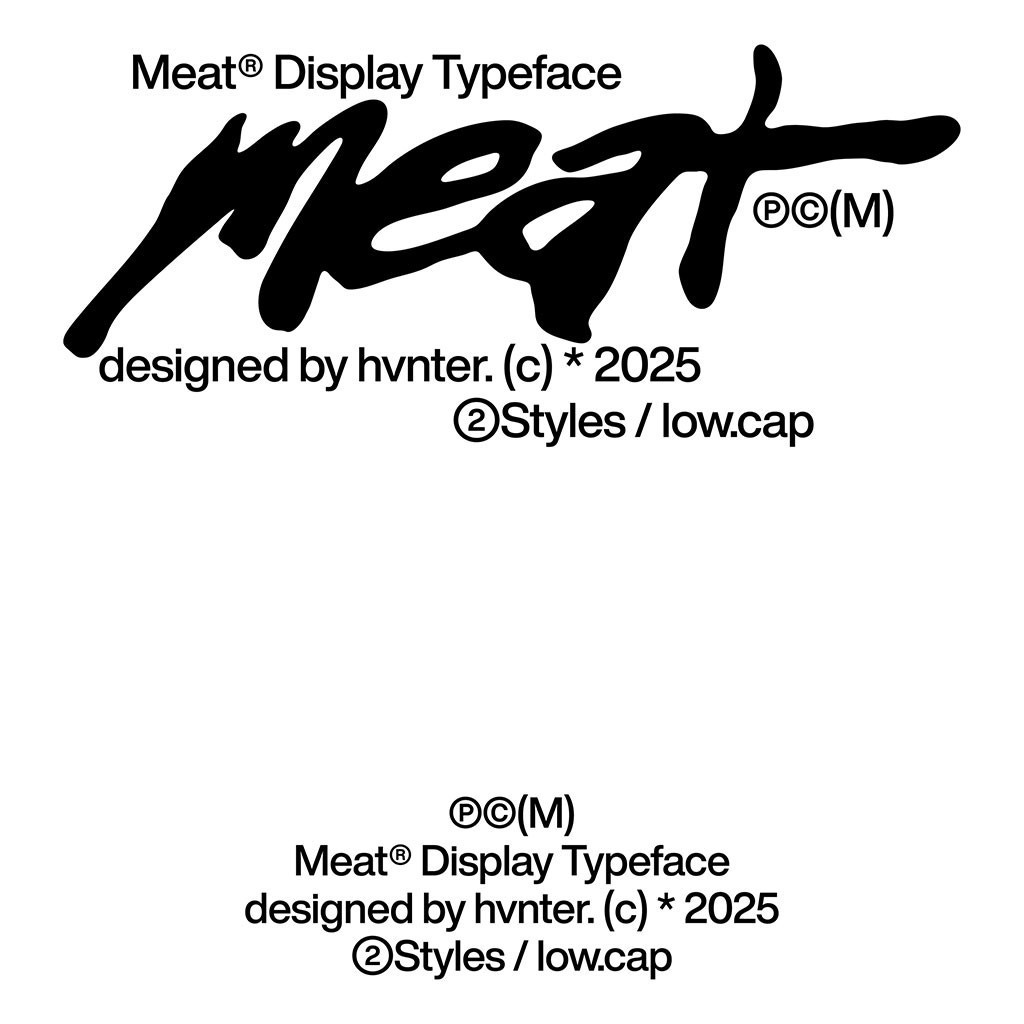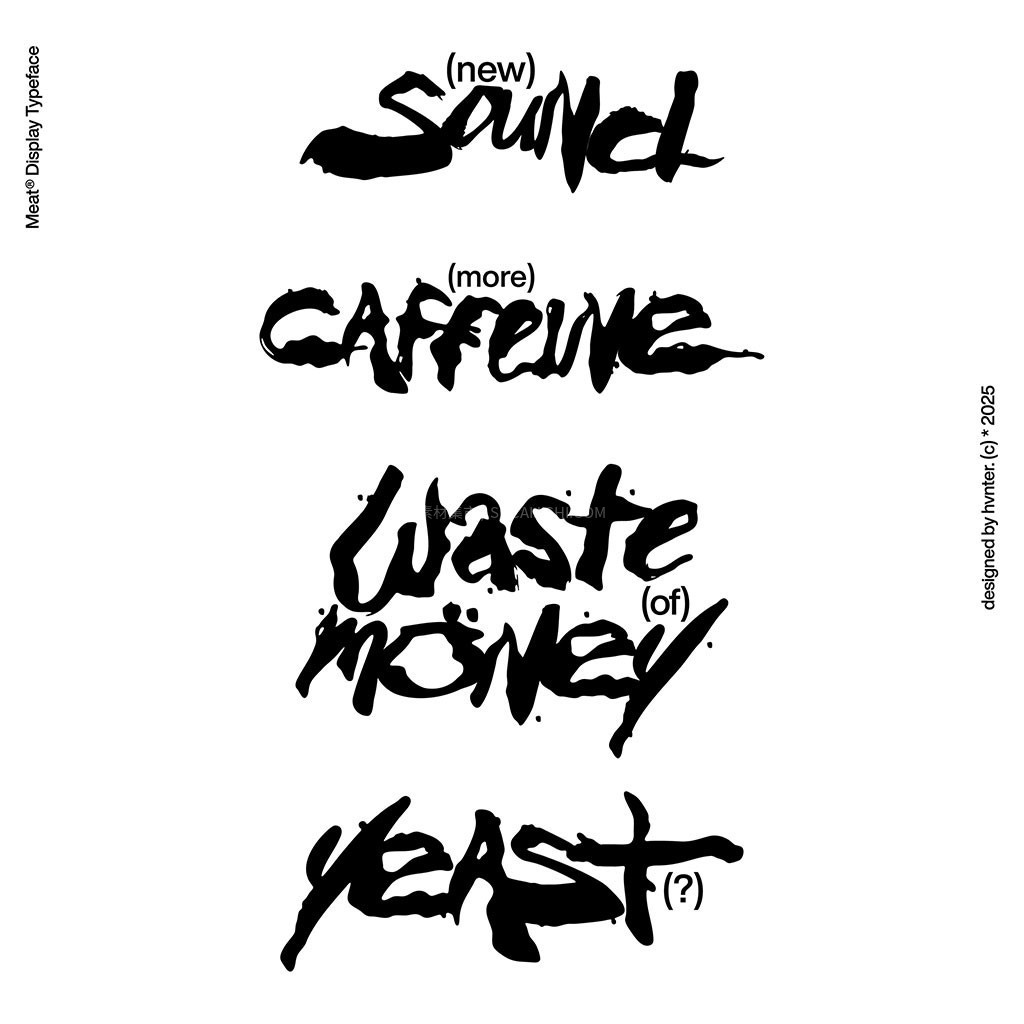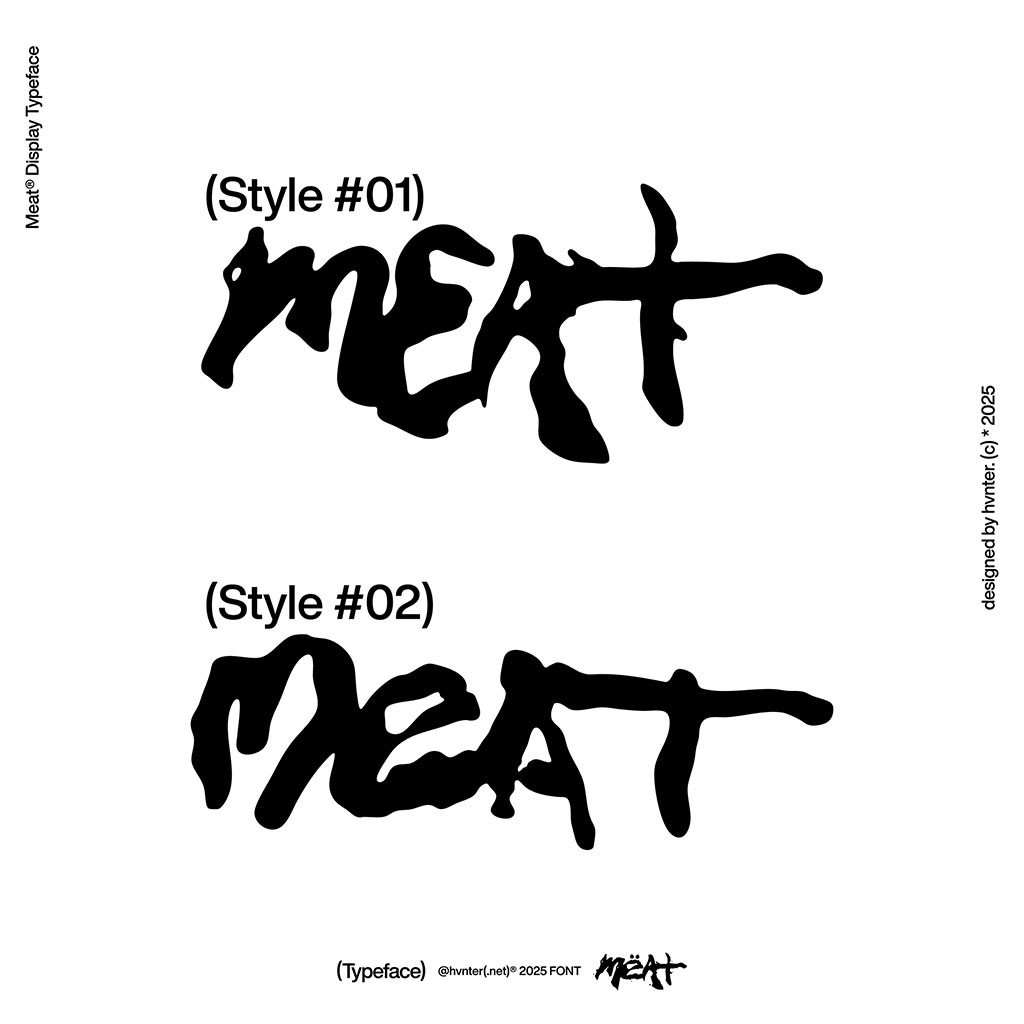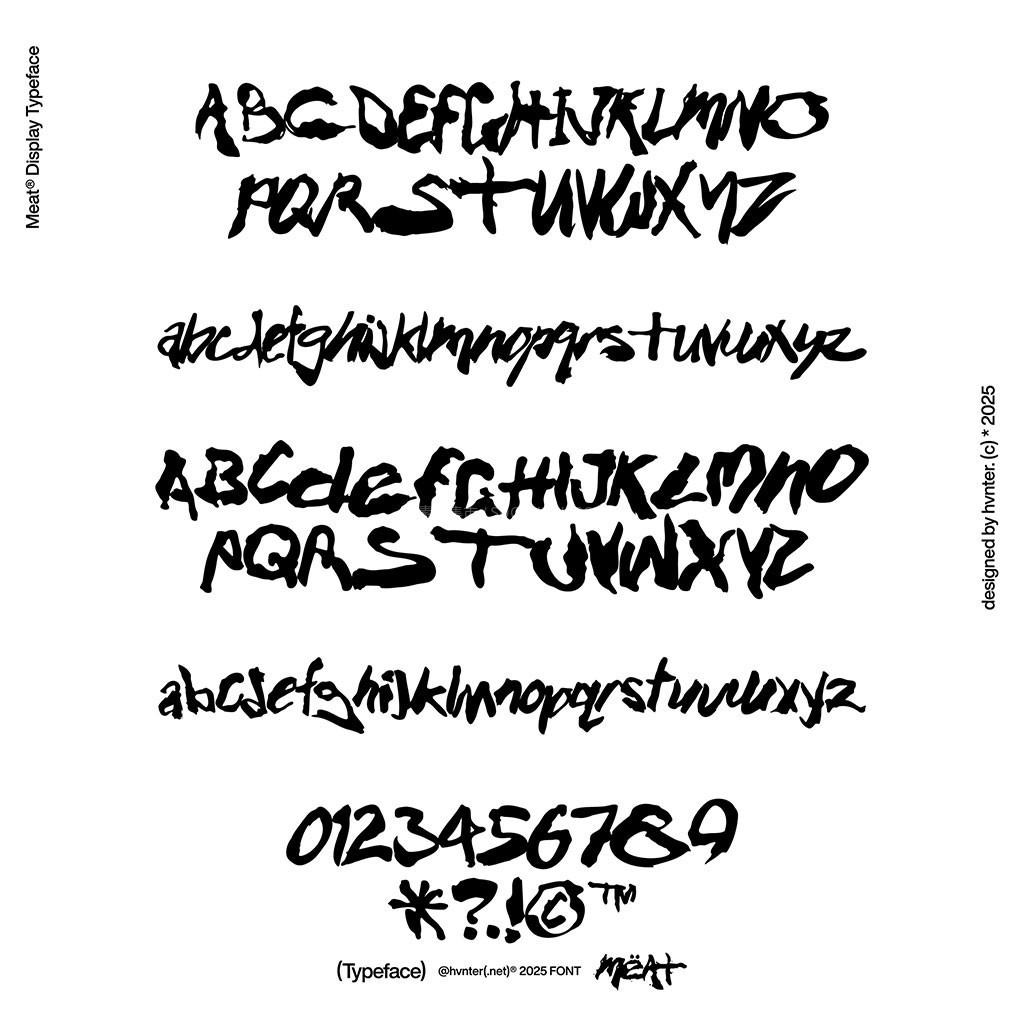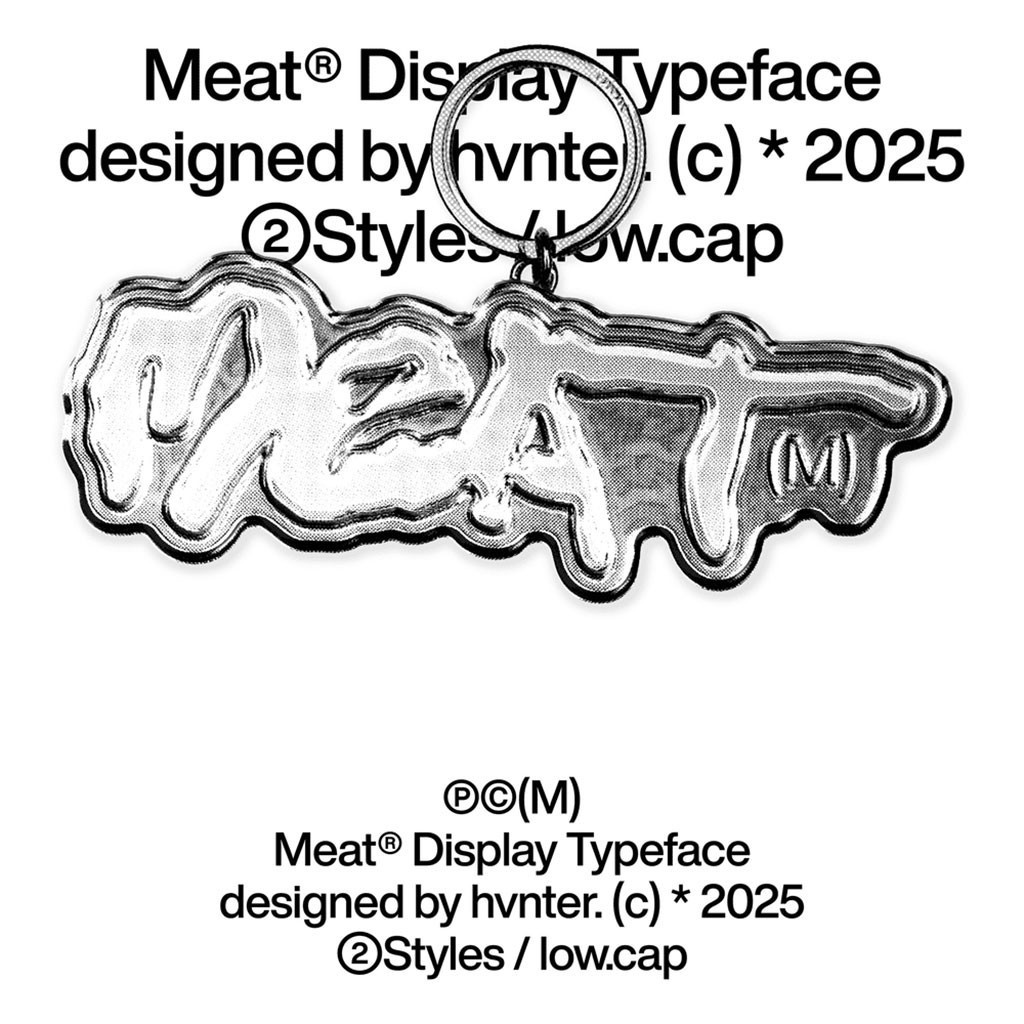
Meat Typeface 酸性粗犷手绘风英文字体
一款超级有生命力的手绘粗犷英文字体——Meat Typeface!这款字体主打一个原生态的手绘质感,线条粗犷有力,视觉冲击力极强。资源内贴心地包含了两种不同的字重,大小写字母 (A-Z, a-z)、数字 (0-9) 以及基础标点符号全部配齐啦!不管是做个性海报还是潮牌视觉,用它排版绝对吸睛,轻松拿捏那种不羁的复古街头范儿~